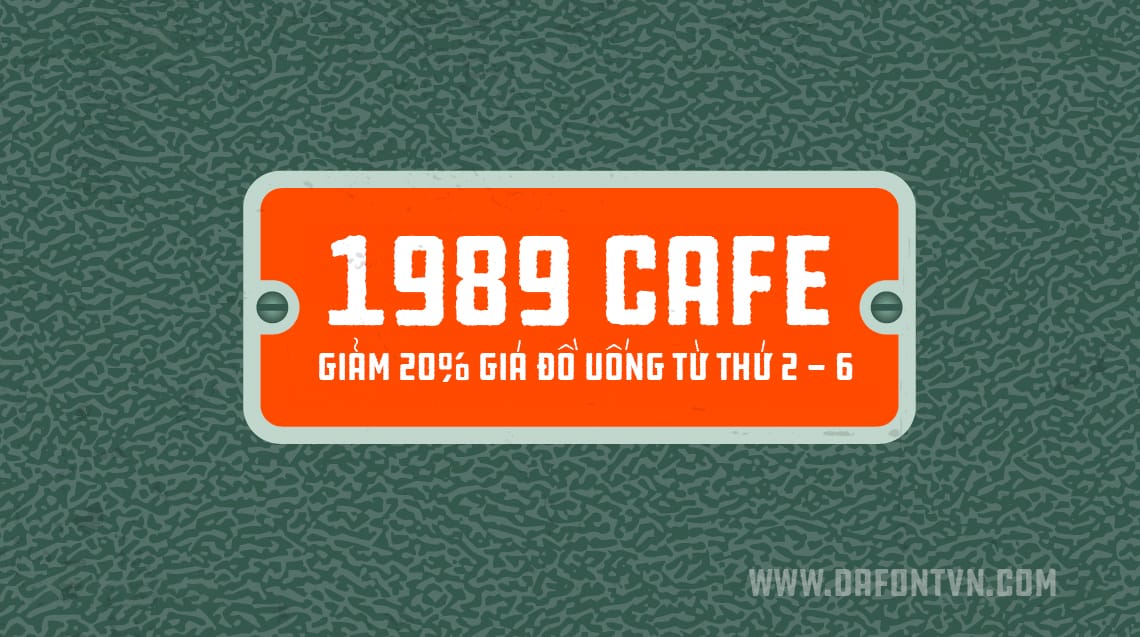
Tải font iCielBC DDC Hardware Rough Việt hóa
Font iCielBC DDC Hardware Rough Việt hóa preview 1
iCielBC DDC Hardware Rough Việt Hóa là một trong những font chữ nằm trong bộ font Hồi Ức Sài Gòn, font được Việt hóa bởi iCiel. DDC Hardware là font gốc nước ngoài với nhiều kiểu dáng khác nhau, nhưng đều có cấu trúc dày, vuông vắn và đơn giản. Với phiên bản Việt hóa, DDC Hardware đã được cách điệu theo phong cách retro để phù hợp với mọi kiểu thiết kế mang phong cách hoài cổ, xưa cũ.
Font iCielBC DDC Hardware Rough Việt hóa preview 2
Font iCielBC DDC Hardware Rough Việt hóa preview 3